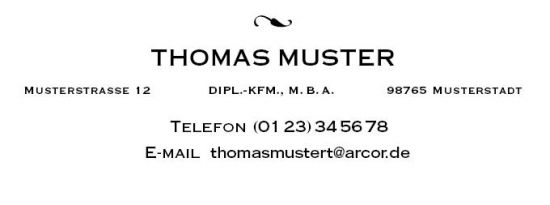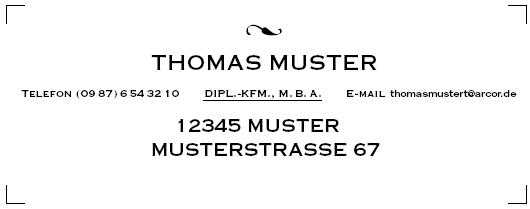
Okay, Ihr habt’s so gewollt:
Aber wie gesagt: mir geht es darum, daß – nachdem mich potentielle Kunden kennengelernt haben, z.B. auf einer Reisemesse – sie den Kontakt wiederfinden, wenn sie ihn brauchen. Und das hat sich für mich bewährt. Beispiel: Gerade heute war ich zu einem Erst-Termin, da hatte ich vor ein paar Tagen nur eine Visitenkarte hinterlassen, weil die Geschäftsführerin nicht im Haus war. Die Geschäftsführerin hatte ich vor über zehn Jahren mal kennengelernt. Sie wußte nun bereits bei der Terminabsprache, wer ich bin. Und als ich dann zum Termin erschien, war bereits klar, daß ich den Auftrag bekomme.
dieses C bei communications würde ich weglassen: Wofür steht das konzeptionell??!! Also weg!
Außerdem hast Du drei Satzkanten, mindestens eine zuviel: g, I und K
Grafik+Design = 3 Fehler: Estens: zu kompress. Zweitens: Keine Matheaufgabe. Drittens: Sieht nach Faulheit aus (zu faul, um »und« auszuschreiben?). Also lieber ganz normal: »Grafik und Design«.
»in Tourismus und Outdoor« (warum nicht »Tourismus+Outdoor« :-)). Mal bitte langsam lesen: »Ihr Spezialist für Grafik in Outdoor«. Holprige Formulierung, nicht?! Auch »Spezialist« ist eigentlich überflüssig: Das hofft man implizit, wenn man so eine Karte bekommt. Also final: »Grafikdesign für Tourismus und Outdoor« oder, wenn Du auch Produktdesign machst: »Grafik und Design für Tourismus und Outdoor«.
Vielleicht auch den Zeilenabstand etwas erhöhen ...
Du siehst auf dem Foto müde aus
ich würde für mich nie eine visitenkarte mit einem bild machen.
falls ich aber einen kunden hätte der sich so was wünscht und es für ihn wichtig ist, z. b. ein callgirl :oops: dann würde ich es als herausforderung sehen. man könnte z. b. ein gutes bild machen, die karte zweiseitig gestalten und zwar auf einem chromolux karton, das bild »fett« glänzend und auf der karton seite die üblichen daten, es könnte sehr gut funktionieren. das bild in s/w und rest in siber und rot.
die verträter masche, auch wenn sie funktioniert, finde ich unsymphatisch und affig.
ich würde für mich nie eine visitenkarte mit einem bild machen.
Es kommt drauf an. Für den Privatgebrauch kann man ganz lustige Sachen machen. Diese Karte mag mein Schwesterherz ganz gern und mir gefällt sie auch:
... also ich muss dem Oliver in seiner Kritik in allen Punkten beipflichten! Außerdem werde ich hier heimlich, still und leise zum TYPOGRAFSKI-Fan => die Arbeiten, die er hier bereits gepostet hat oder die auf seiner Seite zu bestaunen sind, entsprechen aber so etwas von genau dem, was ich mir unter guter Typographie vorstelle, dass es bereits ängstigt. Möglicherweise ist die Luft in Dessau ja noch bauhausgeschwängert, vielleicht ist es aber auch einfach Talent, jedenfalls wäre ich extrem neugierig hier einmal ein paar Beispiele (ohne Bild) zu sehen!
Das Thema ist weit weniger banal, als es klingt. Die Frage, die oben gestellt wurde, finde ich auch durchaus erwägenswert: Welche Informationen sind von Belang? Interessiert den Kunden eines Gestalters wirklich noch seine Adresse? Reichen bei ihm nicht Telefonnummer und E-Mail? Sofern die Adresse tatsächlich einmal von Belang ist, lässt sich diese nach dem ersten E-Mail-Kontakt sicherlich dem Impressum entnehmen. Ich persönlich glaube auch an die (wohl geordneten) Leerflächen einer Visitenkarte -- denke also auch "weniger ist mehr". Dem Ziel wären lediglich NAME, TELEFON und E-MAIL als Information sehr dienlich! Doch kann tatsächlich auf die Anschrift verzichtet werden? Fragen über Fragen!
... auch wenn es einige schön gemachte Visitenkarten mit Foto gäbe, würde ich meine eigenen niemals mit einem Foto 'bestücken':
1. weil nicht jeder so sympathisch oder kompetent aussieht, wie das Foto es auszudrücken vermag oder er selbst es glaubt,
2. weil der Platz auf einer VK ziemlich begrenzt ist und für Kernaussagen der Dienstleistung reserviert sein sollte, denn
3. ist eine mit Informationen überfrachtete VK nie eine gute Werbung.
Für private oder ganz besondere Zwecke ist es bestimmt eine gute Idee. Ansonsten sollte eine Website vorhanden sein, auf der man sein Foto sehr gut platzieren kann. Ein Interessent kann nachschauen, wenn er es möchte oder für notwendig erachtet. Ich mach's jedenfalls so, da auch ich Gesichter rasend schnell vergesse.
Ich glaube der Satz "Form follows function" wird in diesen Tagen 111 Jahre alt. Ist das schon zu lange her? Oder reimt sich "L'art pour l'art" einfach besser?
Ich will jetzt noch mal nachhaken:
Die geäußerte Kritik am Satz meiner Visitenkarte ist natürlich richtig. Beim nächsten mal wird’s besser. :-)
Aber zurück zum Foto. Am Sonnabend war ich auf der ITB – der Internationalen Reisemesse in Berlin. Aussteller und Fachbesucher haben im Halbstundentakt Termine. Fünf Tage lang. Üblicherweise werden die Visitenkarten an die Gesprächsnotizen getackert. Aber manchmal fallen sie wieder ab, oder man hat den Tacker vergessen oder...
Ich hatte sieben Termine, bei dreien wurde geäußert: „Gut, daß ein Foto drauf ist. Da kann im Nachhinein nichts schiefgehen.“ Die Funktion ist hier wichtiger als die Form.
Wie gesagt, ich glaube nicht, daß das Foto standardmäßig drauf soll. Aber in manchen Branchen ist es von Vorteil.
Ja, das mir dem Preis ist sicherlich nicht der schlechteste Grund!
Oliver Twist :roll: :
Logo mit Grafik-Idee, passend zur Wortmarke (GET UP = Chartbreaker = Hit = Pfeil nach oben)
Briefbogen und Visitenkarte mit Zusatzidee (Schweif = Dynamik, zur »Rakete« passend); Visitenkarte passt zum Briefbogen.
Knalliges Pantone-Orange.
Fonts: Garage Gothic, Officina